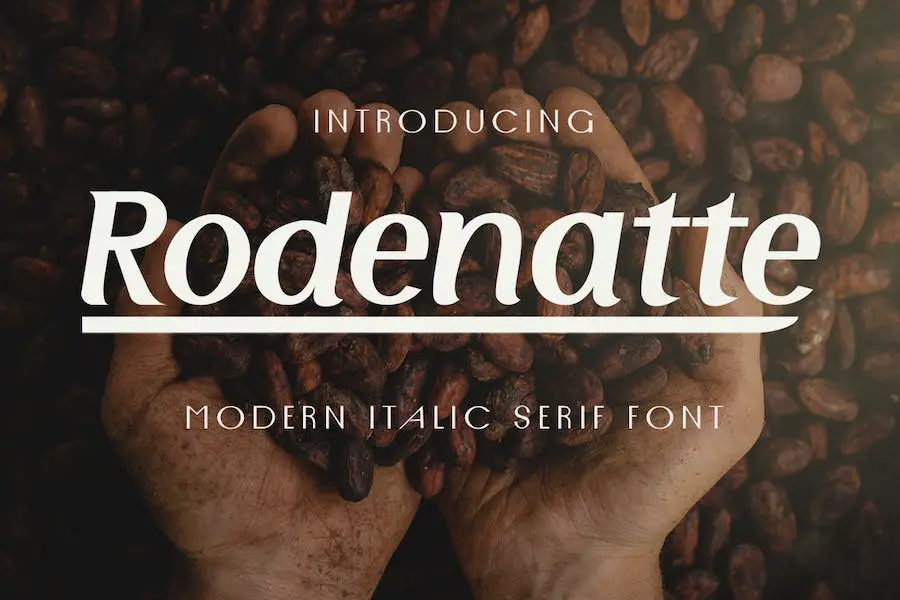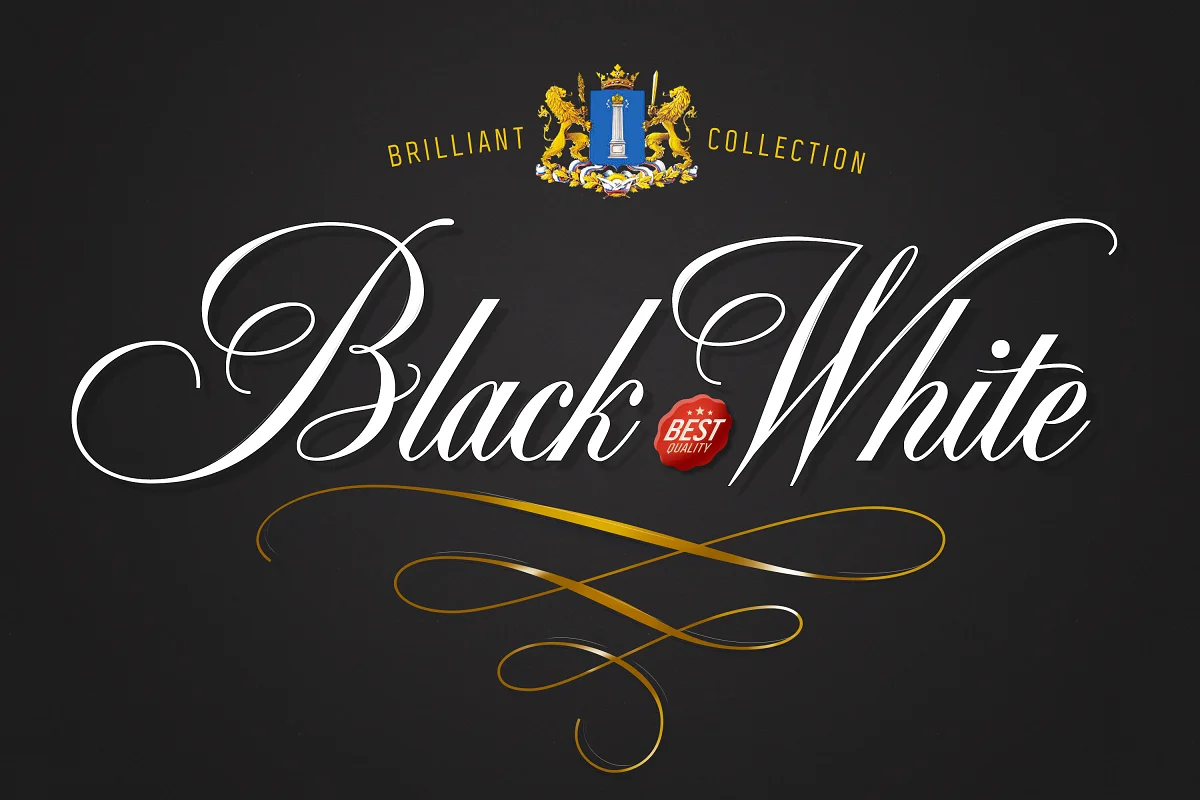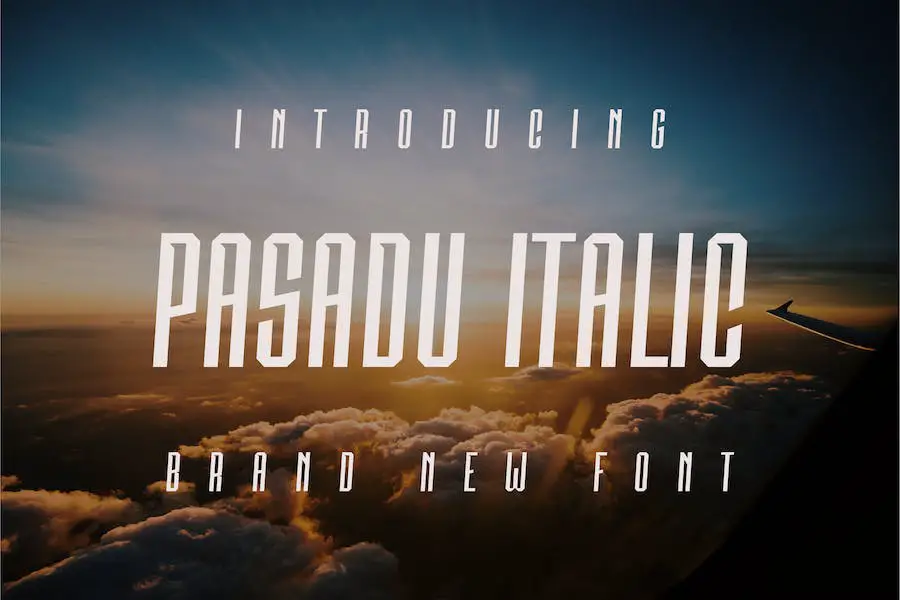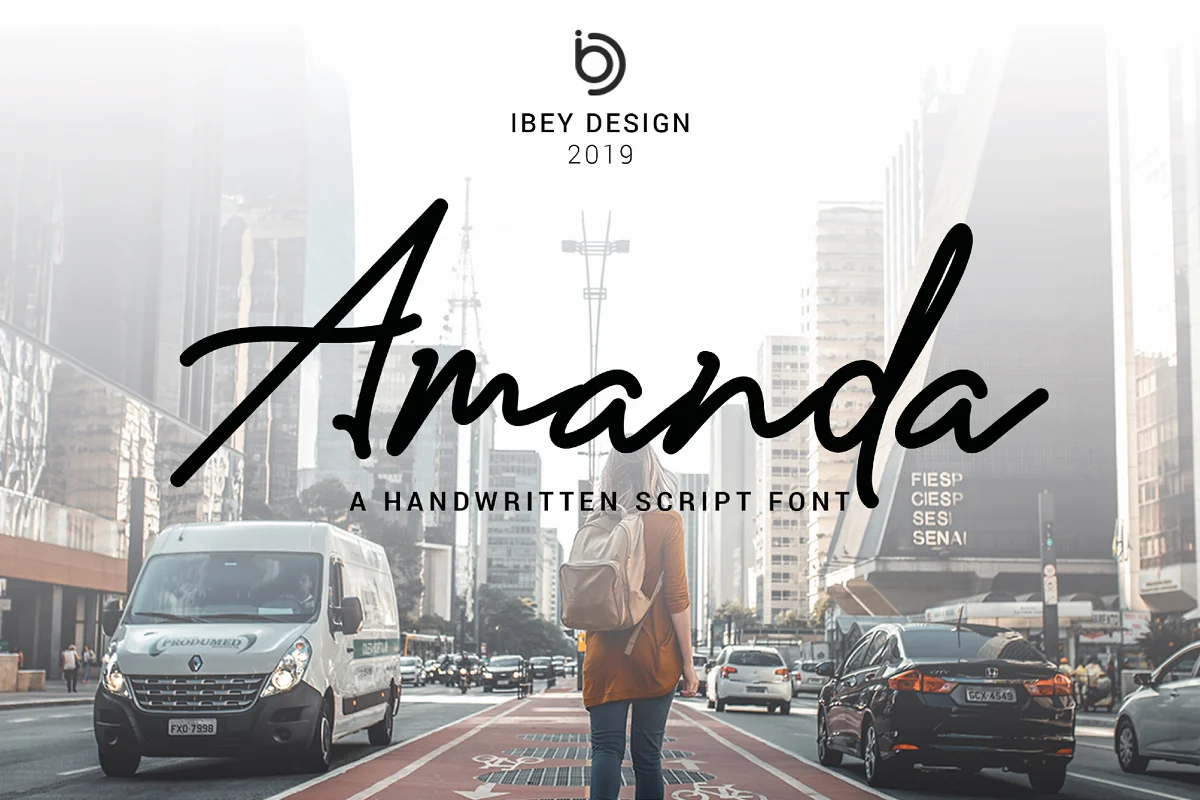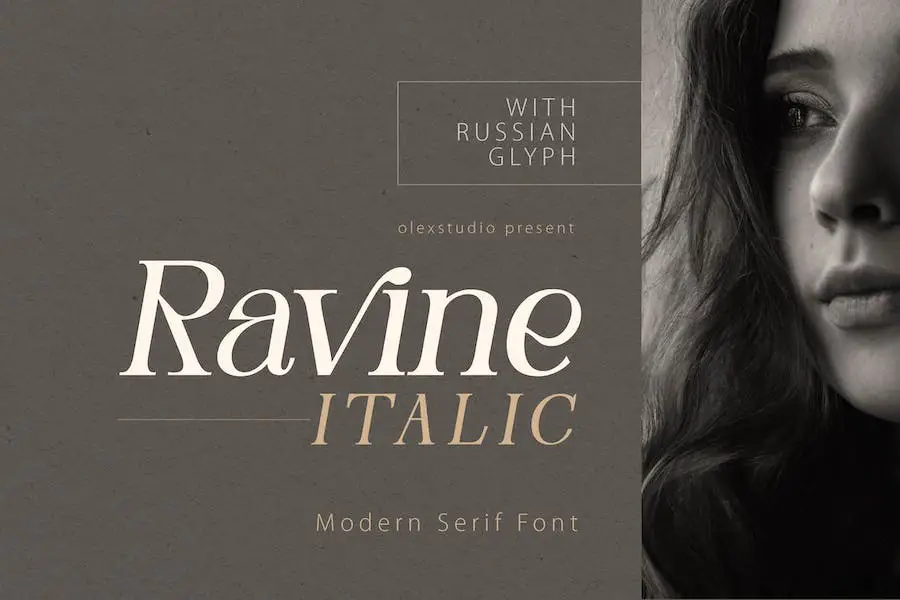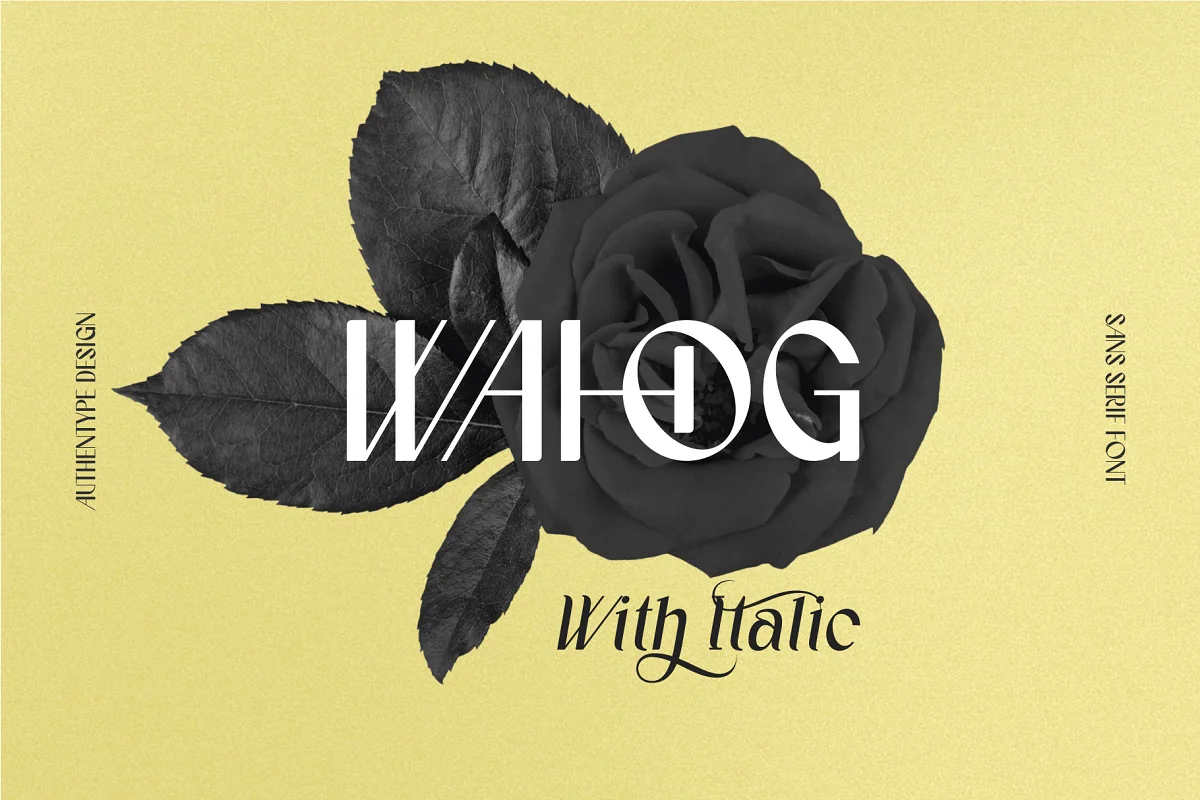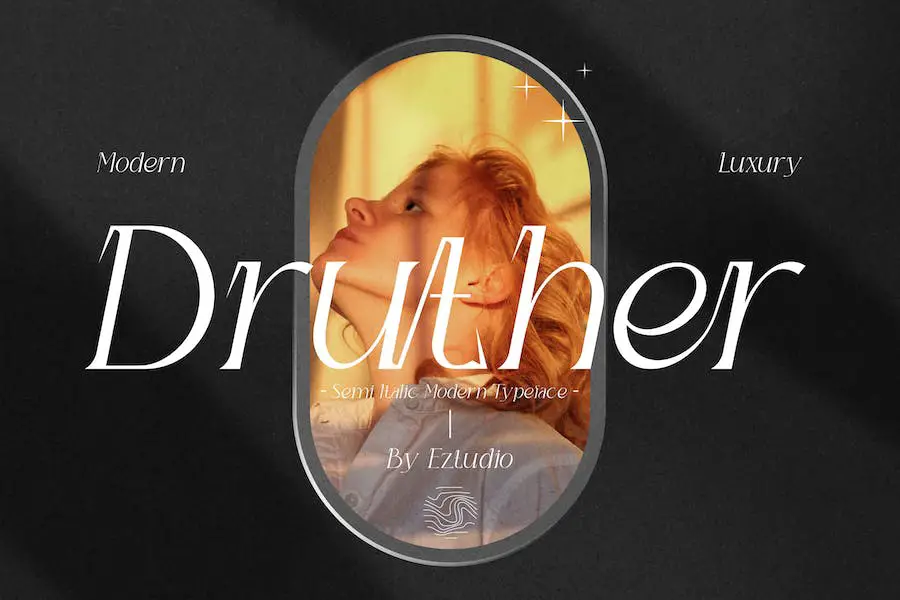
20 migliori caratteri corsivi del 2023 (gratuiti e premium)
Pubblicato: 2023-05-22Hai mai faticato a trovare il carattere corsivo o obliquo perfetto che integri i tuoi progetti di design? Forse è il momento di considerare i caratteri in corsivo! Ma con così tante opzioni là fuori, come fai a sapere quali valgono il tuo tempo e il tuo impegno?
In questo articolo, abbiamo compilato un elenco dei 20 migliori caratteri corsivi che eleveranno i tuoi progetti al livello successivo. Dai classici serif ai moderni sans-serif, questi caratteri offrono versatilità ed eleganza in grado di valorizzare qualsiasi progetto.
Che tu stia progettando un logo, creando materiali di marketing o semplicemente cercando un nuovo carattere tipografico per ravvivare i tuoi progetti, la nostra selezione di caratteri corsivi stimolerà sicuramente la tua creatività. Immergiamoci ed esploriamo alcuni dei caratteri corsivi più belli e funzionali oggi disponibili.
I migliori caratteri corsivi premium
Se sei un graphic designer che cerca di portare i tuoi progetti al livello successivo, ti consigliamo di dare un'occhiata alla nostra selezione dei 20 migliori caratteri corsivi premium. Questi caratteri aggiungeranno sicuramente un ulteriore tocco di eleganza e raffinatezza a qualsiasi progetto di design. Dai un'occhiata e vedi quali attirano la tua attenzione!
Esposizione Fleur
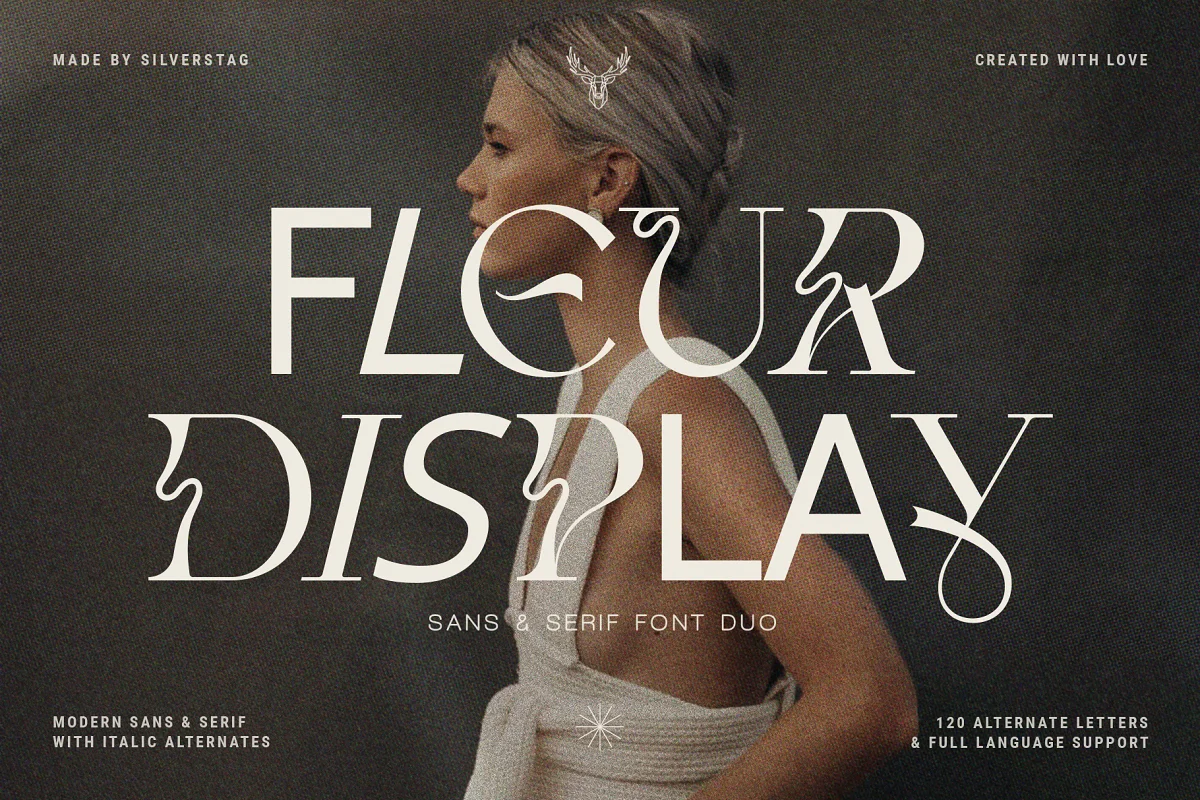
Fleur Display è un duo di caratteri versatile che include sia stili sans che serif, con opzioni di corsivo normale, corsivo, bordato e bordato, tutte disponibili in un carattere tipografico. Questo lo rende perfetto per i grafici che cercano un font che possa essere adattato per adattarsi a una varietà di progetti.
Una delle caratteristiche distintive di Fleur Display è la sua vasta gamma di alternative, con almeno una lettera alternativa disponibile per ogni carattere serif nel font.
Ciò significa che gli utenti hanno molta flessibilità quando si tratta di creare progetti di testo personalizzati e possono passare facilmente tra diverse varianti di singole lettere per ottenere l'effetto desiderato.
Corsivo Ghodain
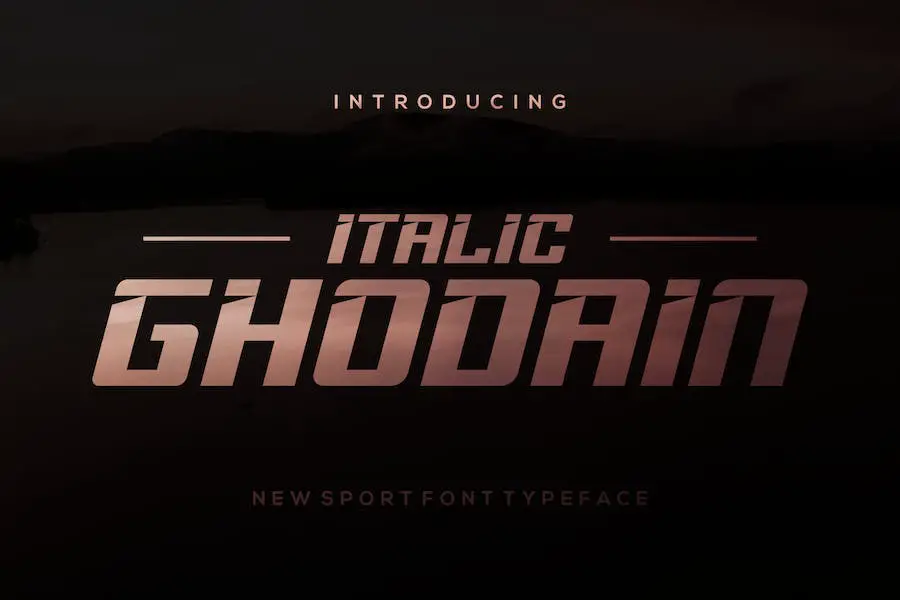
Italic Ghodain è un carattere moderno che offre display audaci e autentici. Questo font è perfetto per vari progetti di branding, come il design del logo, la stampa di t-shirt e i design di eSport. Può facilmente far risaltare il tuo progetto in una vasta gamma di contesti.
Se stai cercando di ottimizzare i tuoi contenuti per Google Italic Fonts, allora Italic Ghodain dovrebbe essere in cima alla tua lista. Con le sue caratteristiche uniche e il design moderno, questo tipo di carattere contribuirà senza dubbio a elevare i tuoi progetti di design al livello successivo.
Atelier Femme
Atelier Femme è un nuovissimo trio di font che combina eleganza e modernità per creare un'esperienza visiva straordinaria per tutte le tue esigenze di design. Il pacchetto include un serif verticale, un corsivo pulito e una sceneggiatura manoscritta casuale.
Supponiamo che tu stia cercando caratteri corsivi di alta qualità per Canva. In tal caso, il trio Atelier Femme è una scelta eccellente per te. Fornisce una combinazione imbattibile di design elegante e moderno, versatilità e funzionalità che faranno risaltare i tuoi progetti dalla massa.
Torsen corsivo
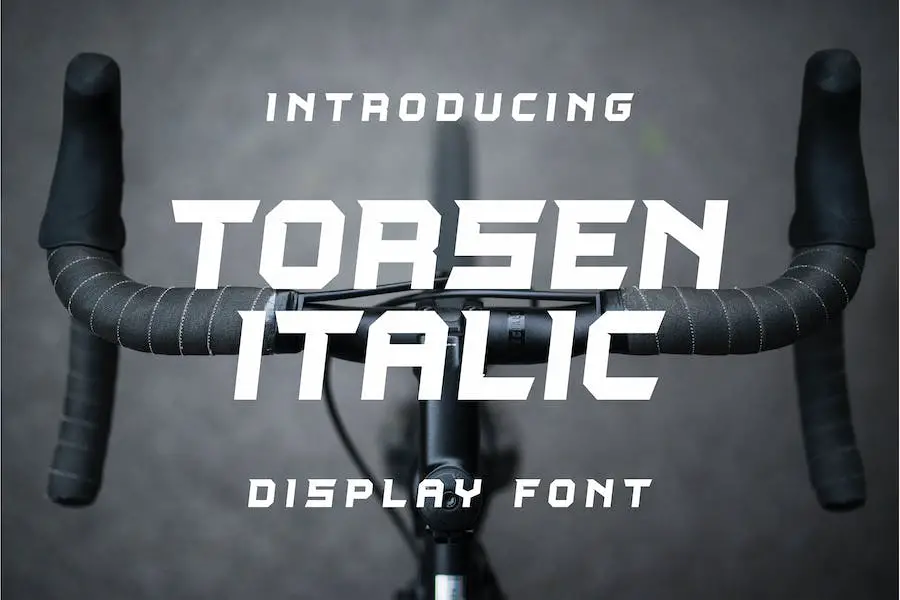
Torsen Italic è un carattere tipografico versatile che può elevare qualsiasi progetto di design. Che si tratti di branding, biglietti da visita, poster, loghi, riviste, copertine, banner, t-shirt o intestazioni, questo font può essere utilizzato senza problemi sia su stampa che su schermo.
Se stai cercando un carattere corsivo che possa aggiungere eleganza e raffinatezza ai tuoi progetti relativi ai circuiti, vale sicuramente la pena prendere in considerazione Torsen Italic.
La sua estetica elegante e moderna lo rende un'ottima scelta per i marchi tecnologici, mentre la sua versatilità gli consente di funzionare bene con una varietà di temi e stili.
Giardino d'argento
Silver Garden è una famiglia di caratteri alla moda e unica disponibile in quattro diverse opzioni: normale, corsivo, grassetto e grassetto corsivo. Il carattere presenta un bellissimo stile serif, che sembra chic ed elegante nelle versioni regolari e in corsivo, ma diventa vintage e nostalgico nelle versioni in grassetto e grassetto in corsivo.
Ognuna di queste versioni di font include oltre 25 legature minuscole e un set completo di alternative di caratteri maiuscoli, insieme al supporto linguistico completo, ai numeri e alla punteggiatura.
Nel complesso, Silver Garden è perfetto per i grafici che cercano una famiglia di caratteri unica e creativa per migliorare i loro progetti.
Che tu stia progettando un invito, un poster, un logo o qualsiasi altra cosa, questa famiglia di caratteri ti aiuterà a creare design straordinari che coinvolgeranno il tuo pubblico. Quindi, se stai cercando caratteri in corsivo per Figma, vale sicuramente la pena considerare Silver Garden.